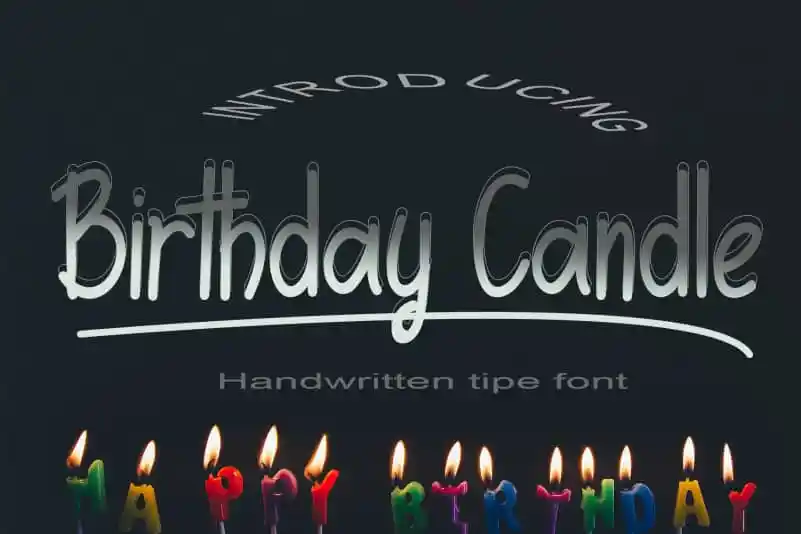
Birthday Candle Display Font – Download Grátis
A fonte ‘Birthday Candle Display Font’ é uma escolha perfeita para quem busca um visual divertido e adaptável. Desenvolvida pelo designer kateengciu, esta fonte feita à mão apresenta caracteres com belas e equilibradas formas. Suas características simples e versáteis permitem que ela se encaixe em uma ampla variedade de designs. O estilo da fonte é tão atraente que você sentir-se-á compelido a usá-la para criar desenhos excepcionais. Perfeito para celebrar festividades como aniversários, esta fonte é um verdadeiro complemento para qualquer projeto criativo. Não hesite em dar vida aos seus projetos de design com essa fonte divertida e adaptável.